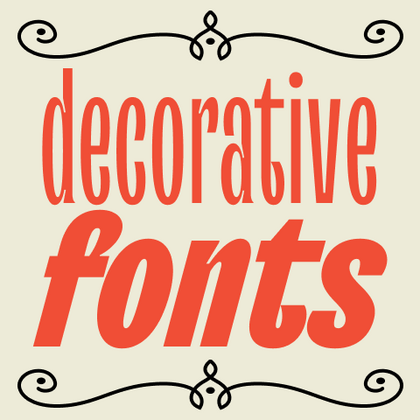
Декоративные шрифты
Когда стандартные решения не впечатляют, декоративные шрифты становятся мощным инструментом визуальной коммуникации. Их отличает эксклюзивный дизайн с уникальными элементами: от изящных вензелей и растительных орнаментов до футуристичных геометрических конструкций. В коллекции TypeType представлены авторские решения для упаковки премиум-товаров, эксклюзивных изданий и fashion-индустрии — шрифты, где каждая буква становится самостоятельным графическим объектом.
TT Polihaus — экспериментальный гротеск, который на первый взгляд кажется обычным, а затем разбирается на части, превращаясь в трафаретный узор.
TT Odellia — старостильная антиква с современным рисунком, вдохновлённая венецианскими шрифтами и классической музыкой.
TT Nooks Serif — акцидентная новостильная антиква с лёгким налётом эгоцентричности. У неё острый и твёрдый, при этом элегантный и статный характер.
TT Chocolates — изящный гуманистический гротеск сo сбалансированными пропорциями, близкими к классическим. Шрифт с приятным дружелюбным характером, который интуитивно воспринимается как что-то знакомое.
TT Nooks Script — шрифт с уникальным рисунком, который не имеет прямых аналогов.
TT Qurdisma — узкий и плотный декоративный шрифт, напоминающий причудливое растение. Вьющиеся, плавные контуры рождают растительный орнамент.
TT Dott — экспериментальный пиксельный гротеск, в котором за основу пикселя взят круг. Это пластичный и необычный акцидентный шрифт, вызывающий ассоциации одновременно с вышивкой и техно-вечеринками.
TT Bells сочетает в себе элегантную мягкость антиквы с непростым и дерзким характером, который выражается в прямых срезах и клинообразных засечках. В основе шрифта лежит ширококонечное перо, характерное для старостильных шрифтов, создающее эти атмосферные срезы и засечки.
TT Jenevers стилистически относится к голландским антиквам нового стиля. В гарнитуре присутствуют характерные детали, свойственные голландским антиквам — это ассиметричная форма засечек или нерегулярный наклон овалов.
В TT Frantz можно найти небольшие отсылки в эстетике арт-деко, которые выражены в сильно заниженной или наоборот сильно завышенной талии у букв. Кроме того, в зависимости от положения ползунка регулировки оси, у некоторых букв изменяется закрытость апертуры.
TT Quaris — изысканная и современная ленточная антиква. Перед разработкой этой гарнитуры мы провели глубокое исследование архетипов ленточных антикв.
TT Ricordi Allegria — современная ленточная антиква, отличительные особенности которой, гиперболизированная разноширинность в пропорциях, контраст между штрихами, клиновидные окончания штрихов и отсутствие традиционных засечек.
TT Bakers — пластичная антиква с нежным и живым характером. Этот шрифт похож на свежую выпечку: он тёплый и мягкий, особенно в жирных начертаниях.
TT Modernoir — акцидентный гротеск с разноширинными пропорциями. Плавные линии и изящные формы ар-нуво в этом шрифте сочетаются с ритмичностью и импровизационной свободой джаза.
TT Ricordi Greto — неконтрастный флорентийский гротеск с динамичными пропорциями. Это единственный гротеск среди антикв в коллекции TT Ricordi, при этом в нем сохранились едва заметные засечки, отсылающие к прототипу.
TT Firs Neue — скандинавский гротеск, сочетающий выразительные графические элементы с универсальностью использования. Мы проанализировали каждый контур и графический элемент. Пересобрали шрифт заново, чтобы сохранить лучшее и исправить необходимое.
TT Gentlemens — динамичный рукописный шрифт, в котором серьёзность и чёткость письма сочетается с элегантностью и изысканностью. У него характер и стиль настоящего джентльмена: сдержанный и всегда уместный, но при этом уверенный и эффектный.
TT Ramillas — стильная и современная антиква. Включает уникальные декоративные начертания и буквицы с цветочным орнаментом.
TT Drugs — ленточная антиква: это шрифт без засечек, но с выраженным контрастом.